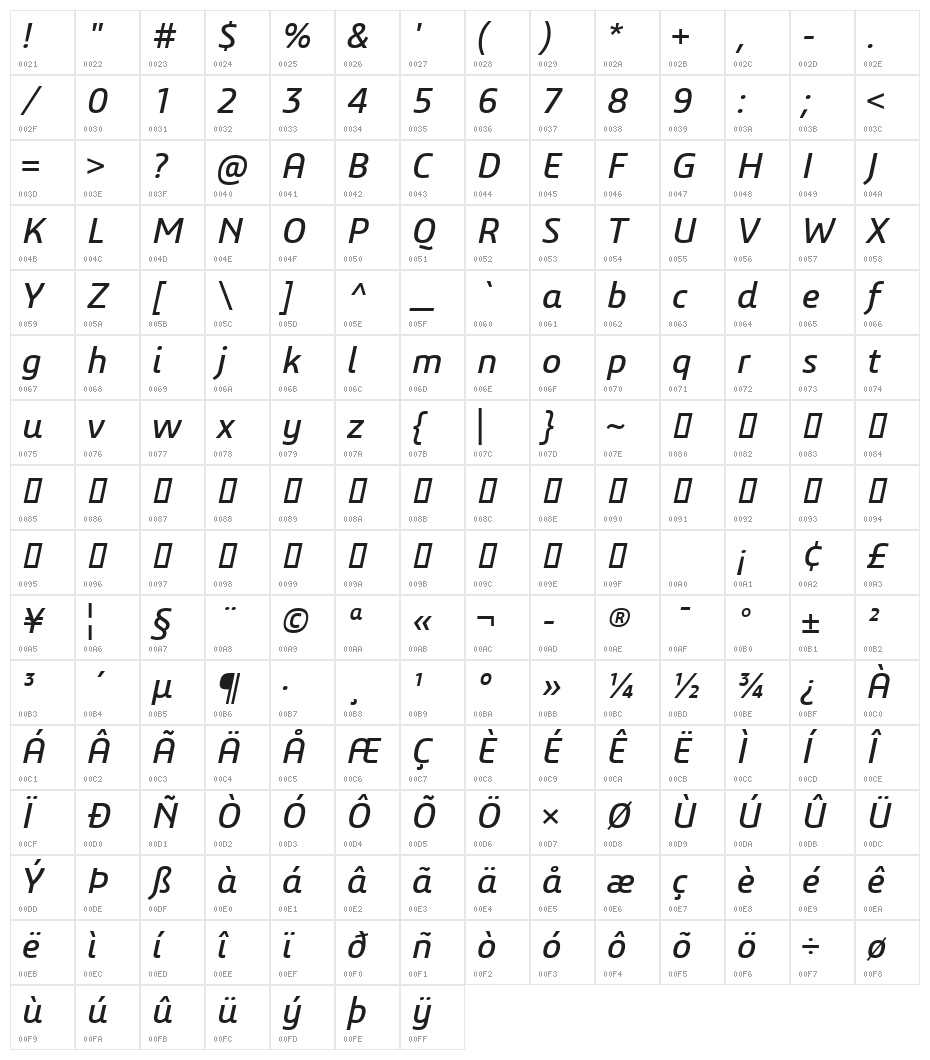
3ds-Italic Font
| Caso d'uso | Headlines, Logos, Digital Media |
| Progetti proposti | Ideal for branding, advertising, and digital media projects that require a modern and dynamic touch. |